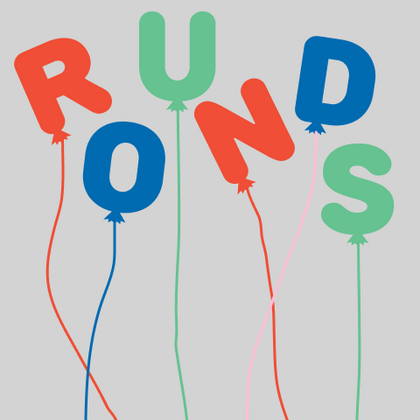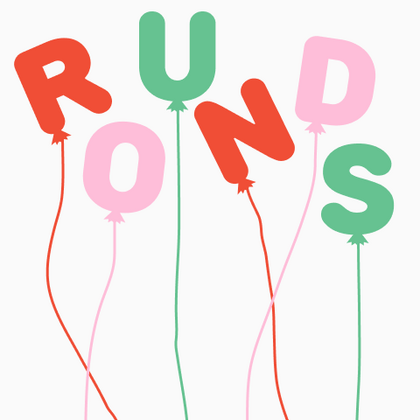
Закруглённые шрифты
TT Nooks Script — шрифт с уникальным рисунком, который не имеет прямых аналогов.
TT Dott — экспериментальный пиксельный гротеск, в котором за основу пикселя взят круг. Это пластичный и необычный акцидентный шрифт, вызывающий ассоциации одновременно с вышивкой и техно-вечеринками.
TT Marks — рукописный шрифт с динамичным ритмом, тёплым характером и слегка ностальгическим настроением. Он вдохновлён классическими американскими расписанными вывесками (sign painting), которые когда-то художники создавали вручную с помощью кистей и красок. Сегодня надписи в таком стиле снова набирают популярность.
TT Travels Next — сверхмодный широкий гротеск. Широкие пропорции — одна из отличительных черт этой гарнитуры: знаки почти не сужаются при переходе от толстого начертания к тонкому.
TT Travels Text — геометрический гротеск с широкими пропорциями. Основные визуальные отличия TT Travels Text — достаточно широкие пропорции и немного сквадраченные формы овалов.
TT Lakes Neue в версии 2.0 — продолжение геометрического гротеска, вдохновлённого финским функционализмом. Новая версия предоставляет больше возможностей, ведь мы не только увеличили кассовый состав и улучшили шрифт технически, но и доработали его визуальный характер.
При проектировании TT Mussels мы уделили большое внимание возможности верстать большие массивы текста и можем ответственно заявить, что TT Mussels является редким видом технологических текстовых шрифтов.
TT Knickerbockers Grotesk символизирует собой монументальность, выраженную в как в традиционной исторической застройке Нью-Йорка, так и в его небоскрёбах. Энергия, постоянное движение и круглосуточная жизнь Нью-Йорка — все это отразилось в нашем TT Knickerbockers Script.
TT Polls берет свое начало как современный модульный брусковый шрифт. При создании шрифтового семейства TT Polls мы держали в голове его использование в дизайне на спортивную тематику, но финальная версия TT Polls отлично подходит и для более казуального дизайна и сфер применения.